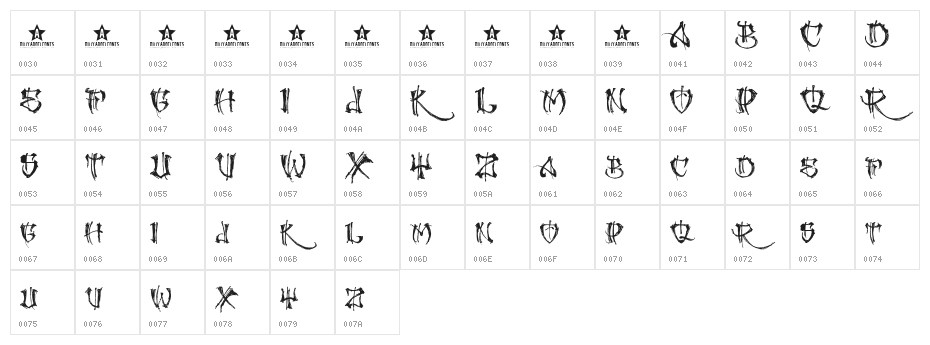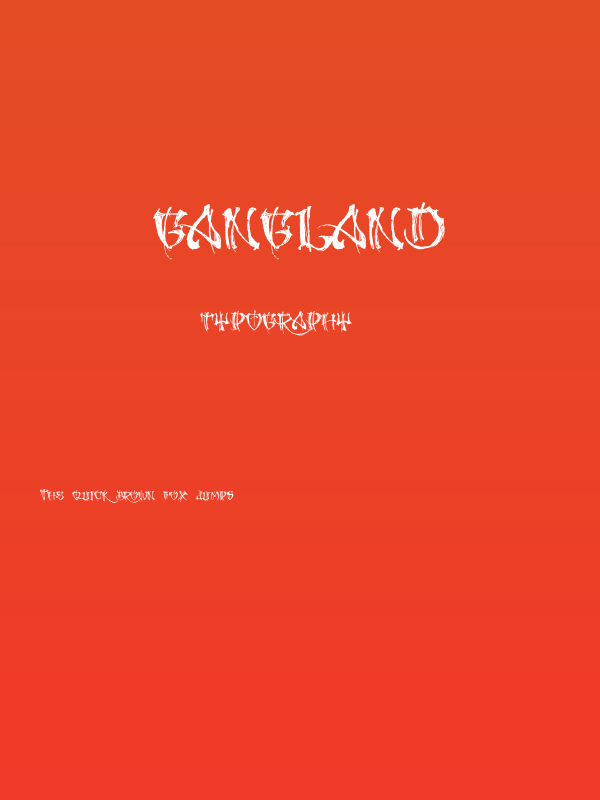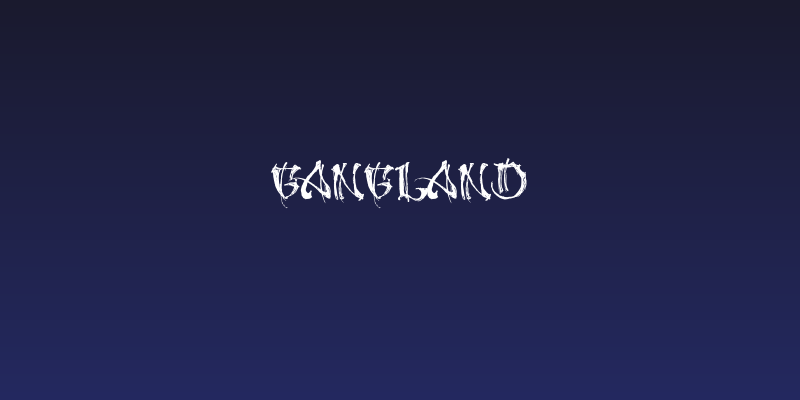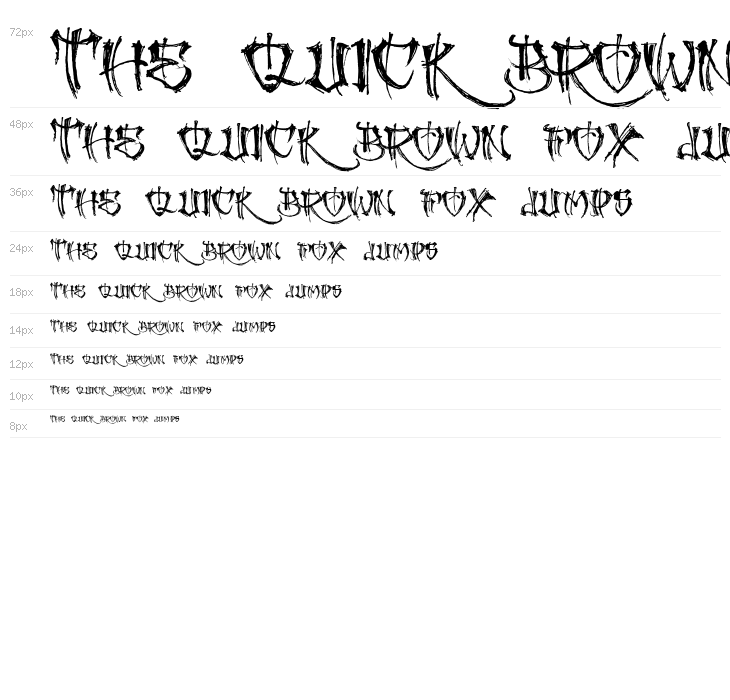
GANGLAND Font
| Proiecte propuse | Ideal for album covers, posters, tattoos, streetwear branding, and any project requiring a bold, rebellious aesthetic. |